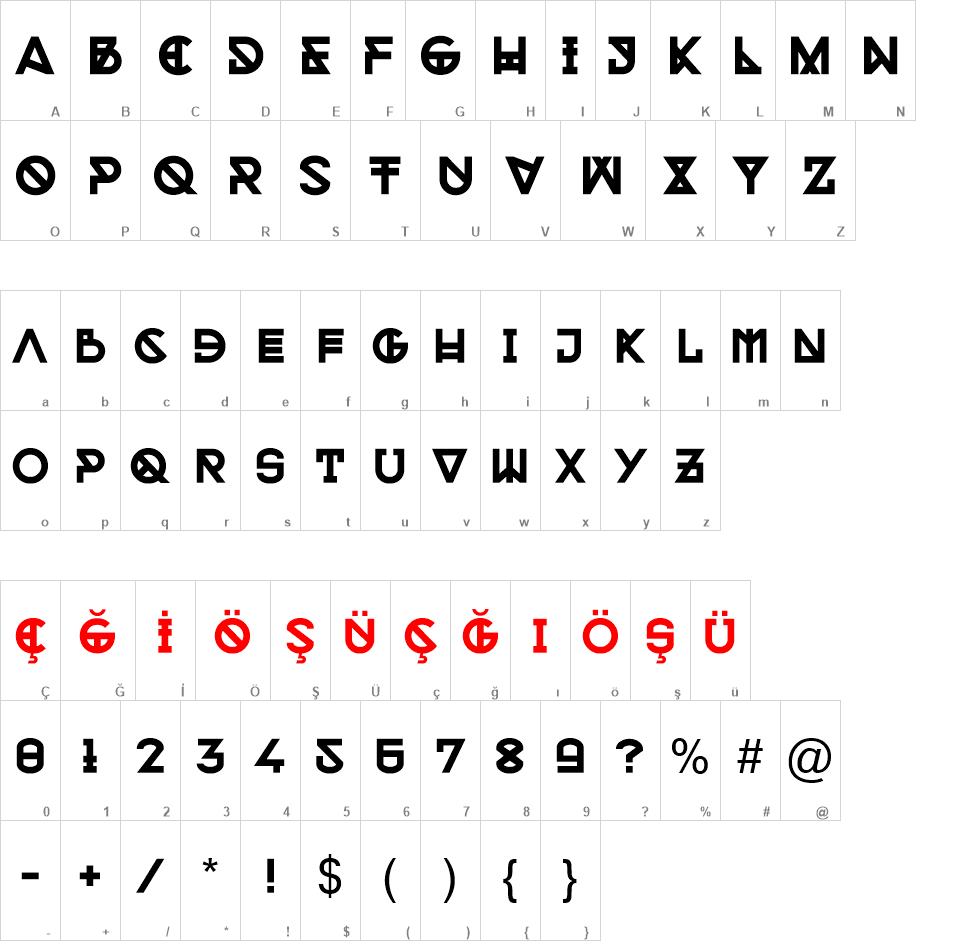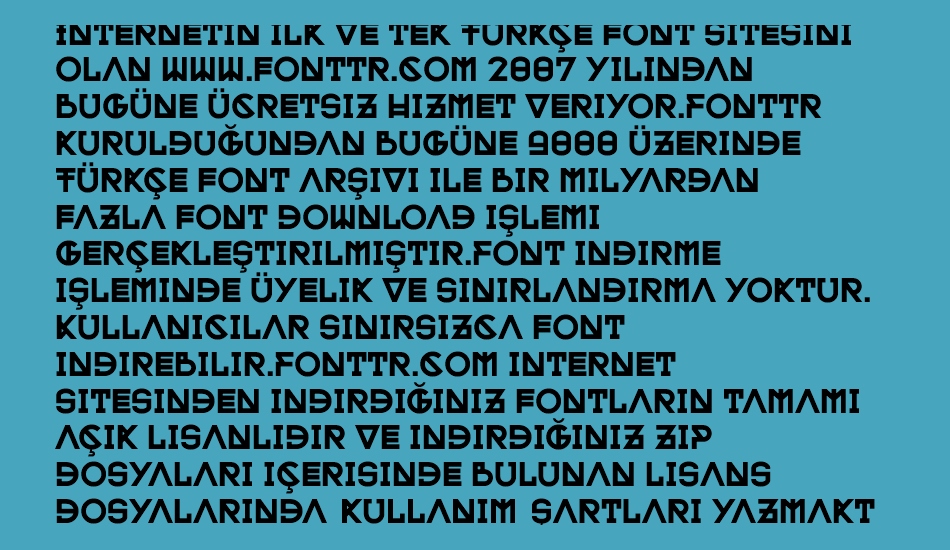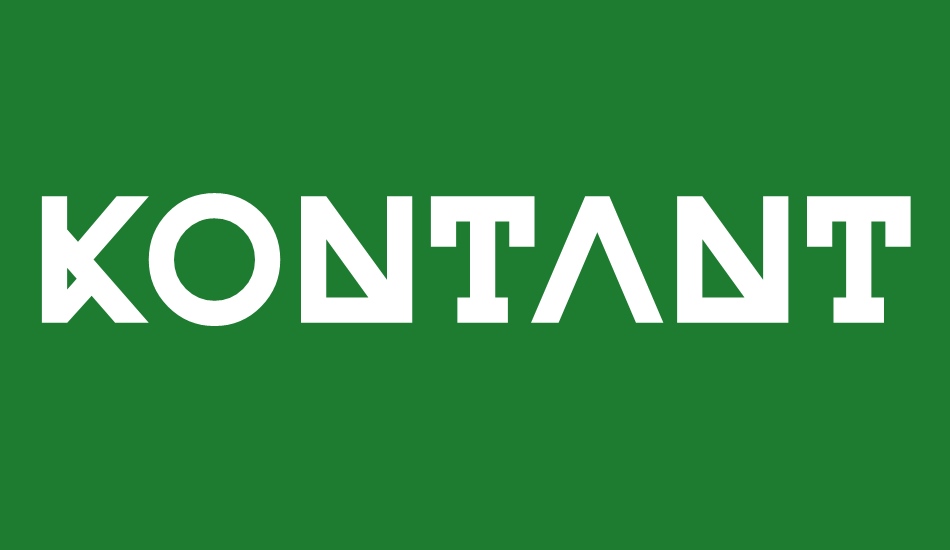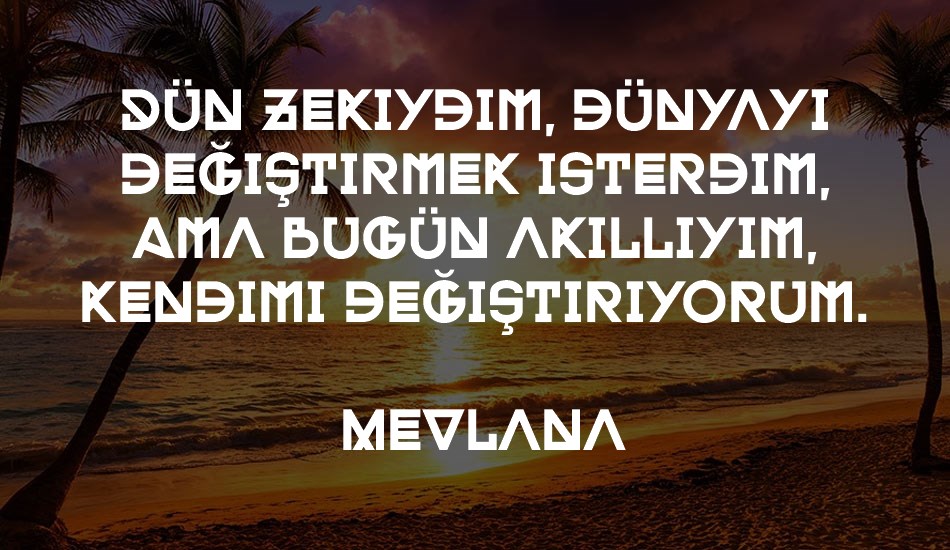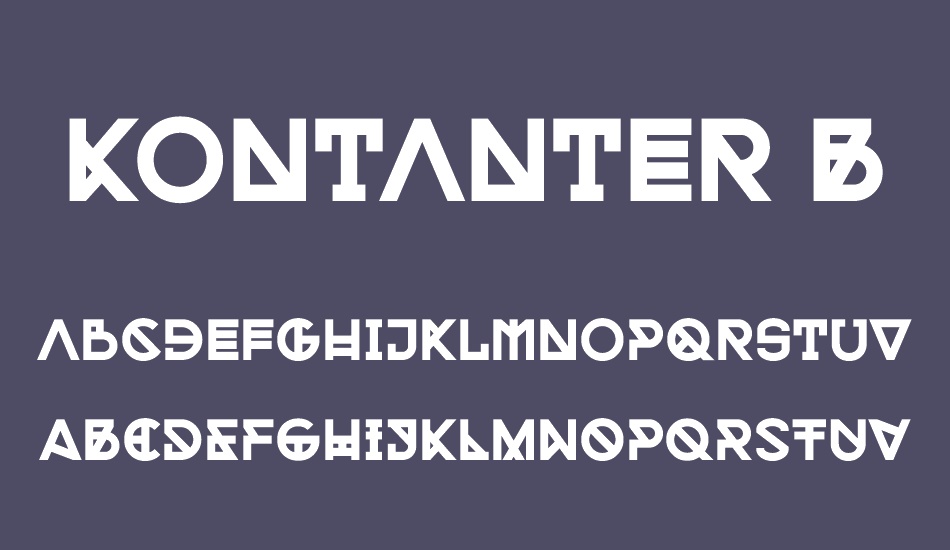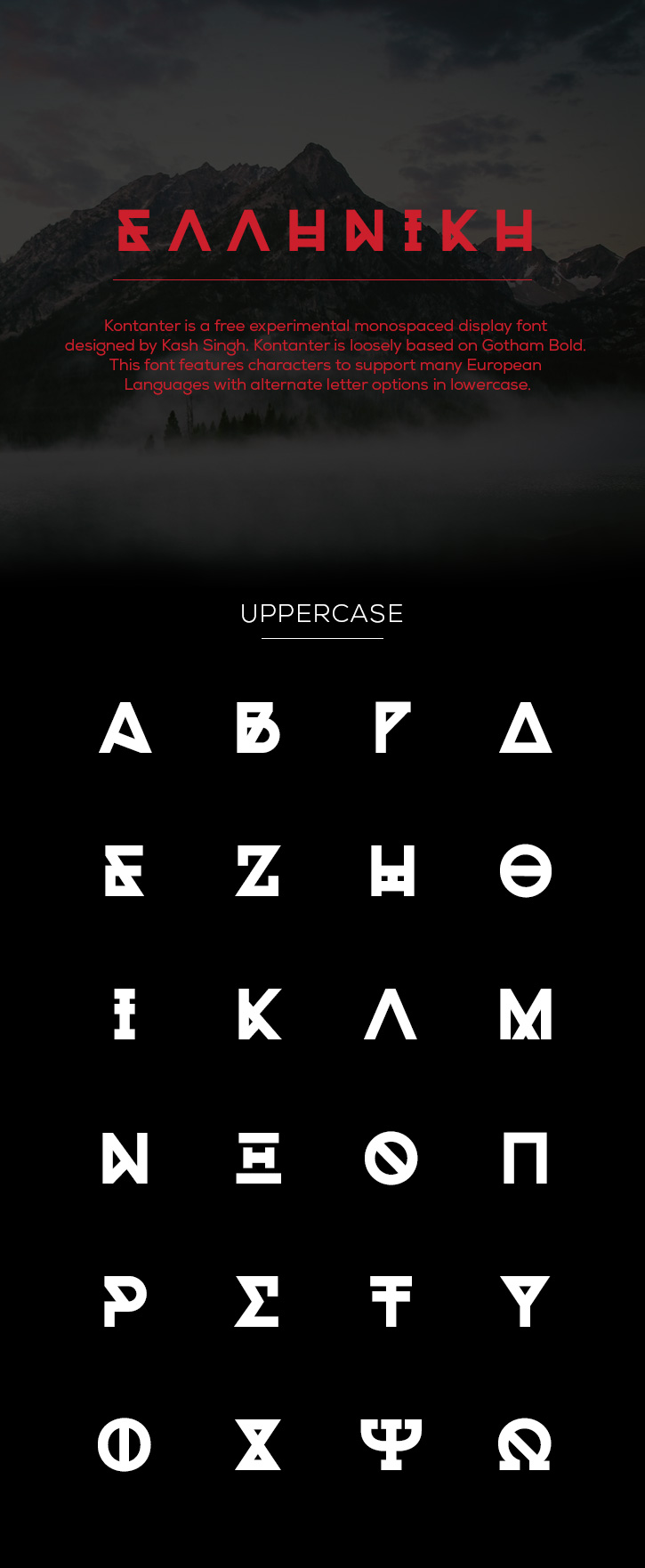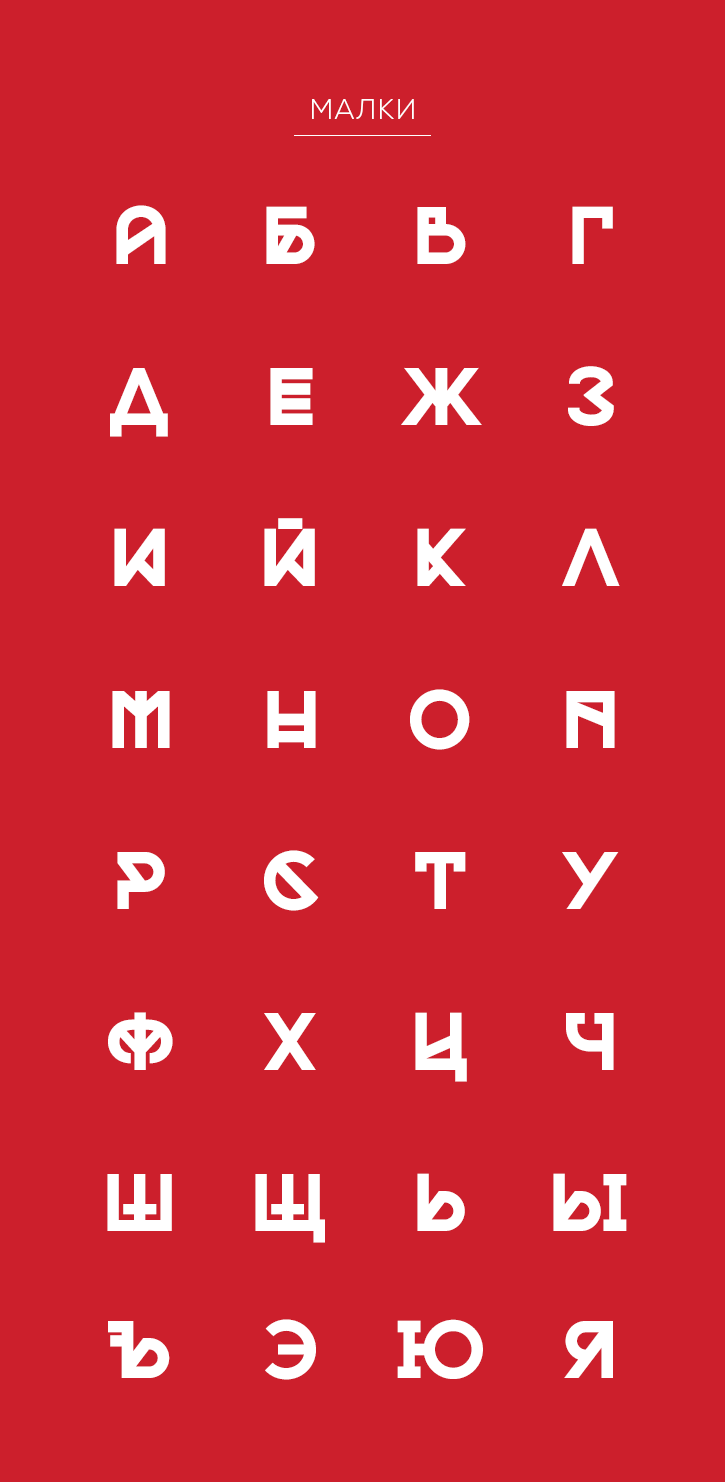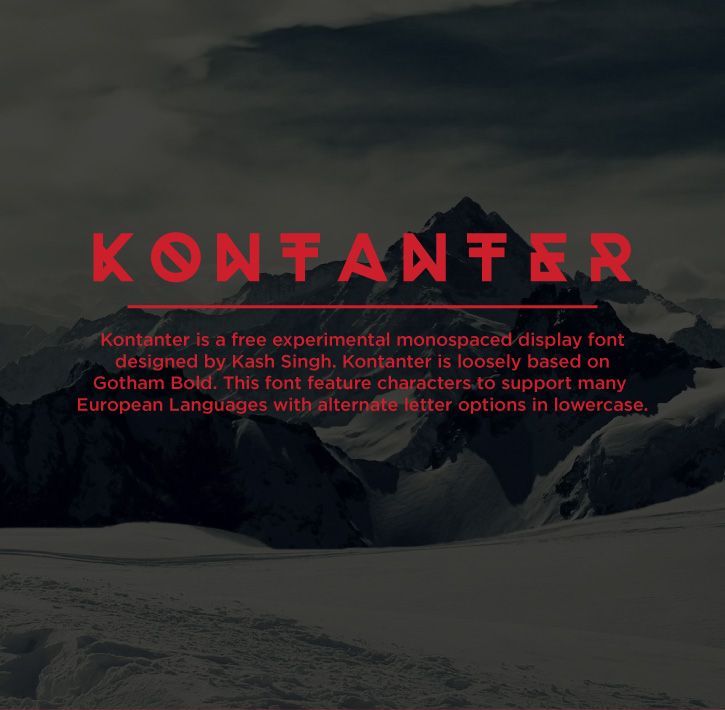
Kontanter font
Kontanter, Kash Singh tarafından tasarlanmış, deneysel olarak duran serbestçe yazılmış bir yazı tipi biçimidir. Bu yazı gevşek Gotham Bold'a dayanıyor. Kontanter, birçok Avrupa dilini küçük harfli alternatif harf seçenekleriyle destekleyen özellik karakterlerine sahiptir. Yazı tipi ayrıca Bulgarca, Rusça, Yunanca ve daha pek çok şeyi betimlemektedir.
Kontanter Bold font